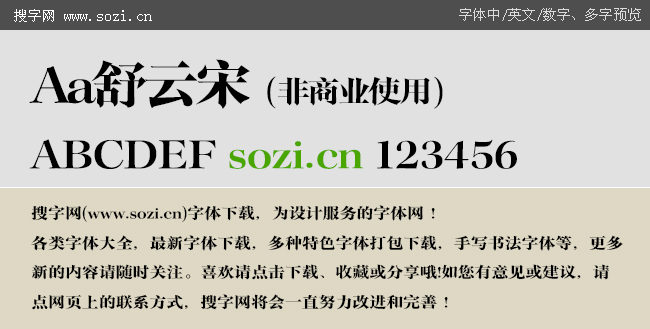
Aa舒云宋
搜字網(wǎng)給大家提供一款A(yù)a舒云宋(非商業(yè)使用)中文字體下載,Aa舒云宋是一款不錯(cuò)的宋體字體,字體簡(jiǎn)潔大方,字形端正,具有很好的視覺(jué)感,適合應(yīng)用于藝術(shù)設(shè)計(jì)、平面宣傳設(shè)計(jì)、網(wǎng)頁(yè)設(shè)計(jì)、海報(bào)設(shè)計(jì)等應(yīng)用(此字體為個(gè)人非商用版,商用可以聯(lián)系QQ:1006760504)。